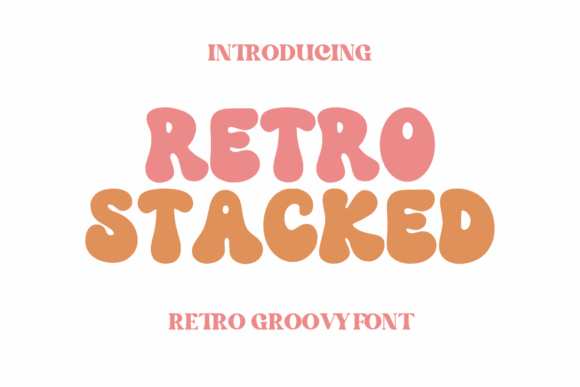
Retro Stacked
Retro Stacked – A Fonte Retro que Transforma Seu Projeto
Se você está em busca de uma fonte divertida e cheia de nostalgia, Retro Stacked é a escolha ideal. Com seu estilo vintage e traços empilhados, ela adiciona um toque cheerful e animado a qualquer peça criativa. Ideal para capas de livros, cartazes, embalagens, merchandise, logotipos e muito mais, esta tipografia garante que seu design se destaque imediatamente.
Por que escolher a Retro Stacked?
- Estilo único e retro: combina linhas grossas com camadas sobrepostas que remetem aos anos 70‑80.
- Versatilidade de uso: perfeita para book covers, posters, embalagens, produtos promocionais e logotipos.
- Legibilidade garantida: apesar do visual descontraído, a fonte mantém clareza em tamanhos pequenos e grandes.
- Impacto visual: cria uma atmosfera alegre e nostálgica que captura a atenção do público-alvo.
Aplicações práticas da Retro Stacked
Ao integrar a Retro Stacked nos seus projetos, você pode:
- Desenvolver capas de livros que chamem a atenção nas prateleiras virtuais.
- Projetar posters de eventos com um visual vintage que gera expectativa.
- Personalizar embalagens de produtos para destacar a identidade da marca.
- Criar merchandise (camisetas, canecas, adesivos) com um estilo retro que vende.
- Construir logotipos que transmitam personalidade e nostalgia.
Retro Stacked não é apenas mais uma tipografia; é uma ferramenta poderosa que traz alegria e carisma a qualquer projeto. Seja para book covers, posters, embalagens ou logotipos, ela garante um visual marcante e memorável. Não perca a oportunidade de incorporar esta fonte retro ao seu próximo design e impulsionar tanto a criatividade quanto o desempenho SEO do seu site.